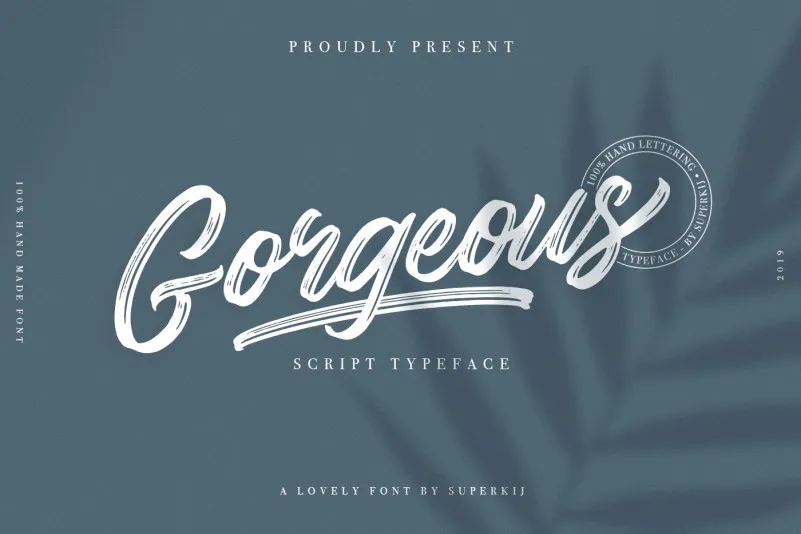
Gorgeous – Script Typeface – Fonte Grátis
Gorgeous - Script Typeface
Aqui está uma versão descritiva para a página de download da fonte ‘Gorgeous – Script Typeface’, adaptada ao estilo solicitado: Descubra agora a incrível Gorgeous Script Typeface Font, projetada pelo talentoso designer superkij. Esta fonte é um toque refinado e autêntico, perfeitamente desenhada para uso em títulos de design ou qualquer outra necessidade que exija uma gravação profunda e personalizada. Adhi Nugraha foi o criador desta elegante fonte brush, repleta de textura forte. Perfeita para decorar seus trabalhos com estilo único, essa fonte oferece um toque diferenciado às suas criações digitais. A Gorgeous Script Typeface é perfeitamente adaptada para uso em anúncios, logotipos e outros materiais gráficos que exigem uma sensação de arte livre e personalizada. O design brush desta fonte é o ideal para designers gráficos ou web, oferecendo um toque sofisticado aos seus projetos. Não hesite em experimentar Gorgeous Script Typeface e transforme seu trabalho em algo único e autêntico.